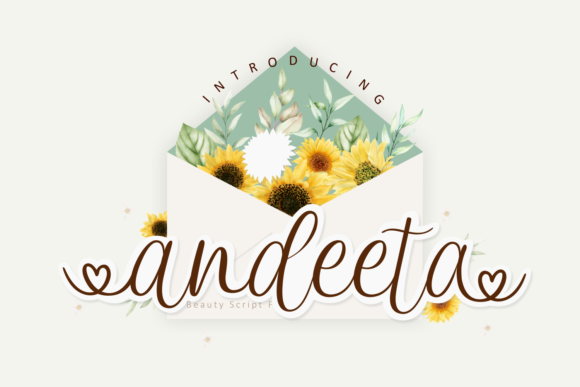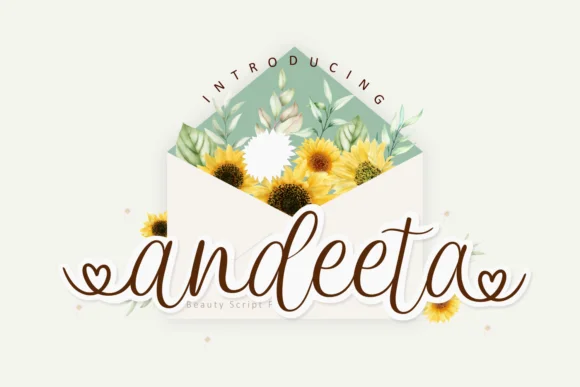
Название: Andeeta Font (2021)
Andeeta - шикарный, изысканный шрифт, излучающий утонченность и элегантность.
Стильные чередования и лигатуры делают этот шрифт идеальным для любого проекта.